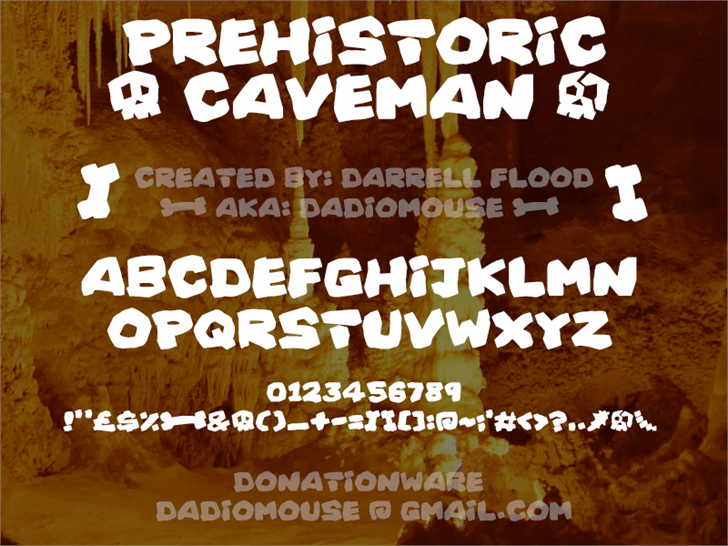
A fonte “Prehistoric Caveman” foi criada usando a High Logic Scanahand por Darrell Flood. Esta tipografia é uma excelente escolha para aqueles que desejam incorporar um toque antigo e arcaico em seus projetos digitais, sejam eles websites, materiais impressos ou até mesmo artesanato digital. Seu design inspirado nos primeiros habitantes da Terra remete a épocas passadas, oferecendo uma paleta de características únicas que se torna perfeita para um estilo gráfico retro e arcaico. Como menciona o designer Hamilton, esta fonte é gratuita para uso pessoal, mas sempre encorajamos qualquer doação que você possa desejar dar, mesmo que seja apenas por gentileza. E como todos os recursos gráficos de alta qualidade da High Logic Scanahand, “Prehistoric Caveman” oferece um design fluido e detalhado que certamente será uma fonte de inspiração para muitos projetistas digitais.